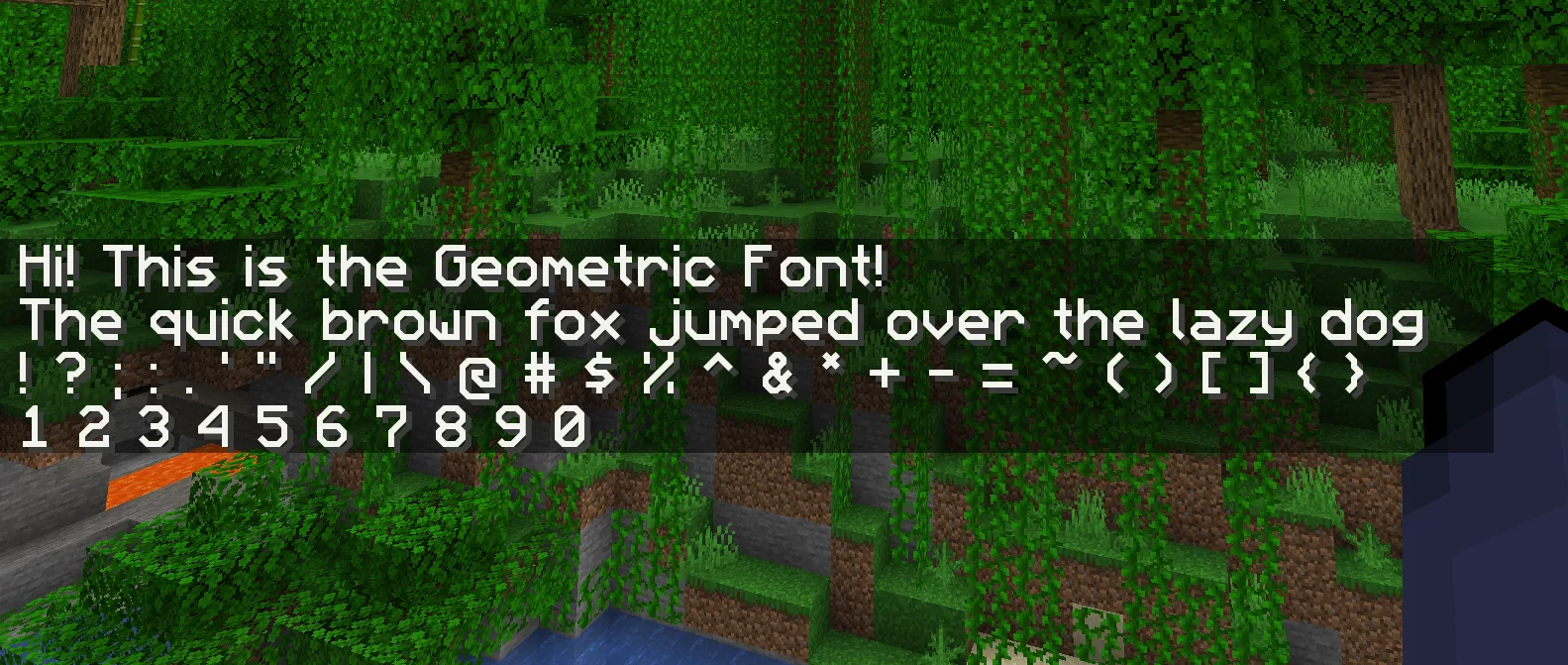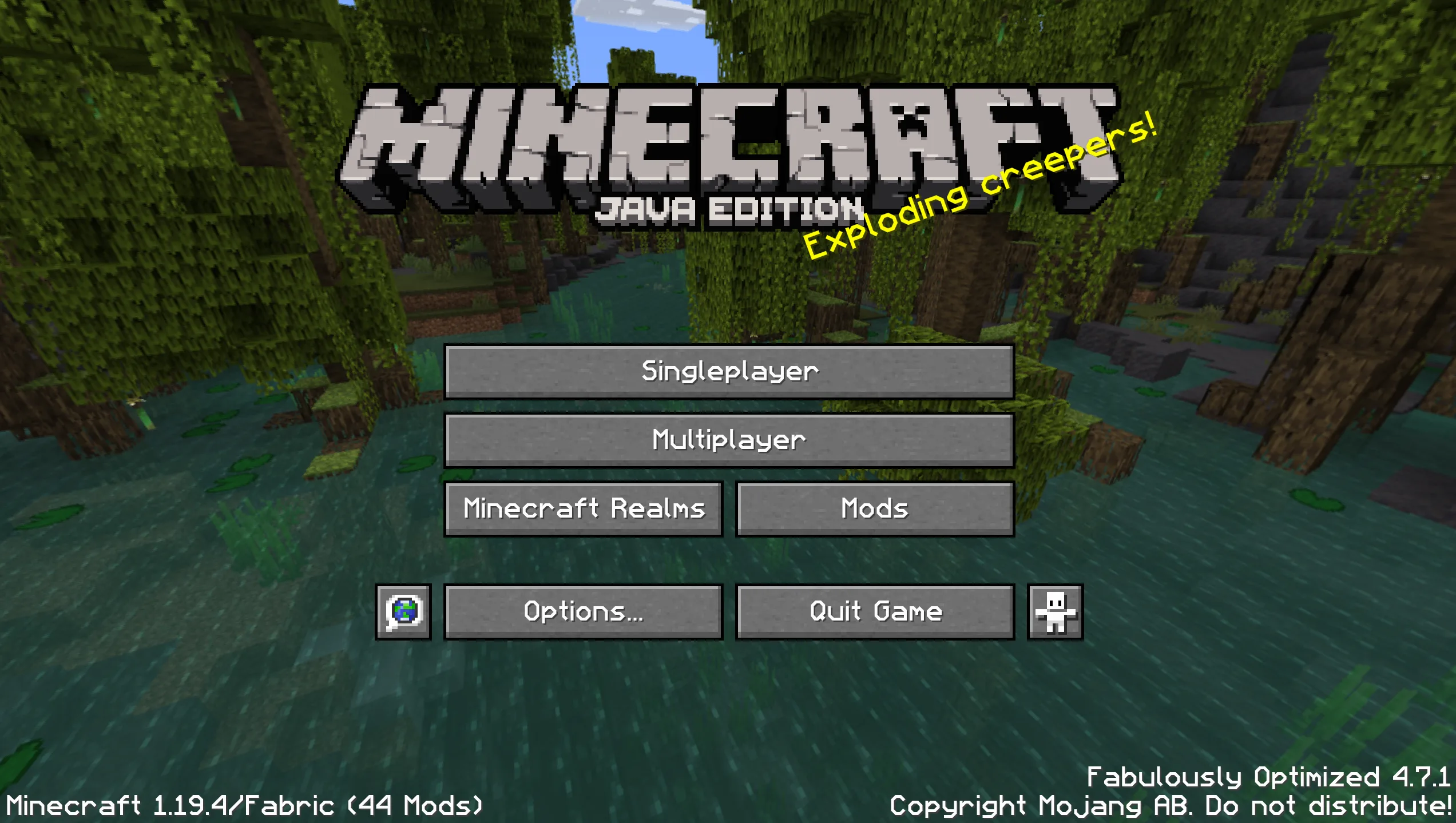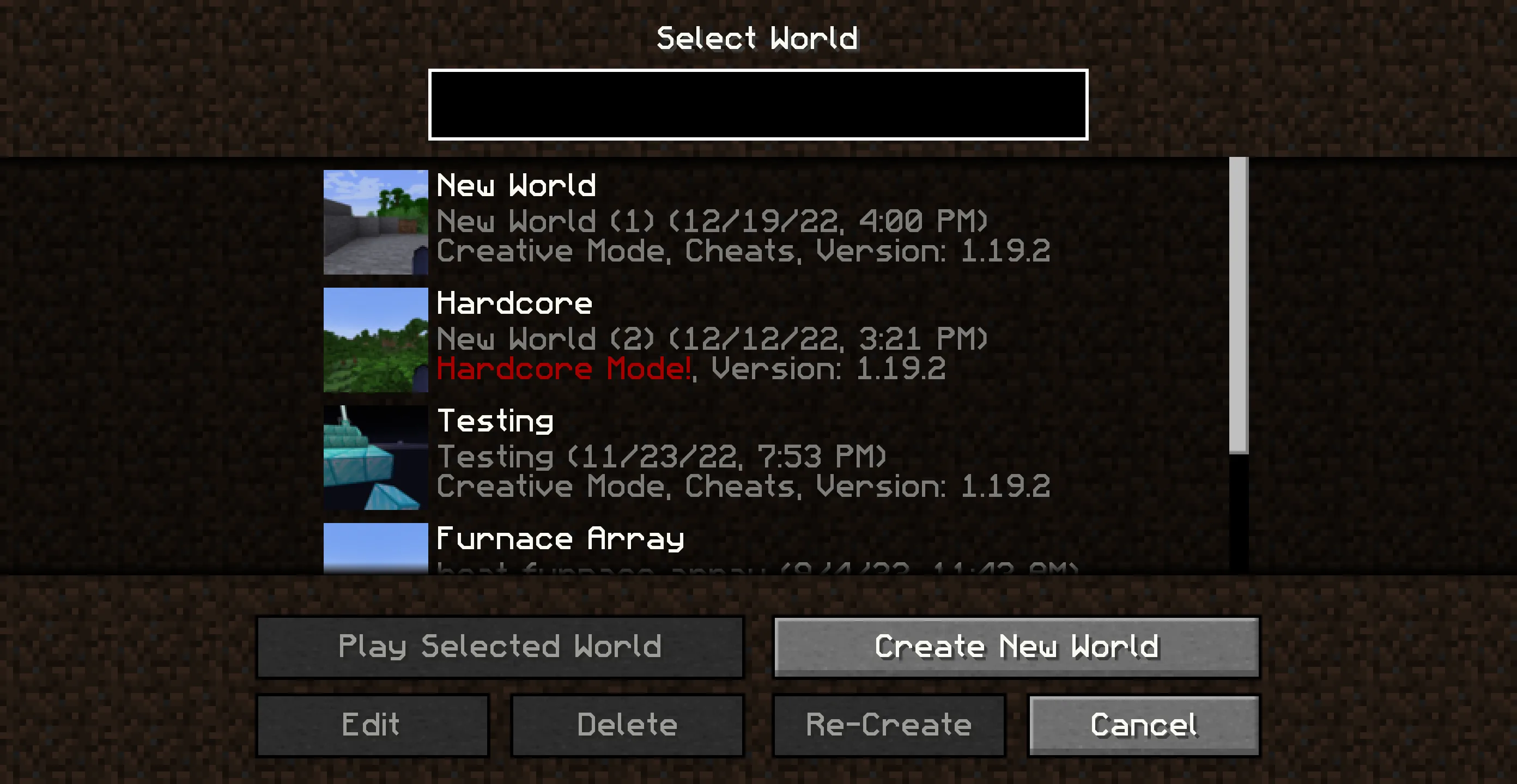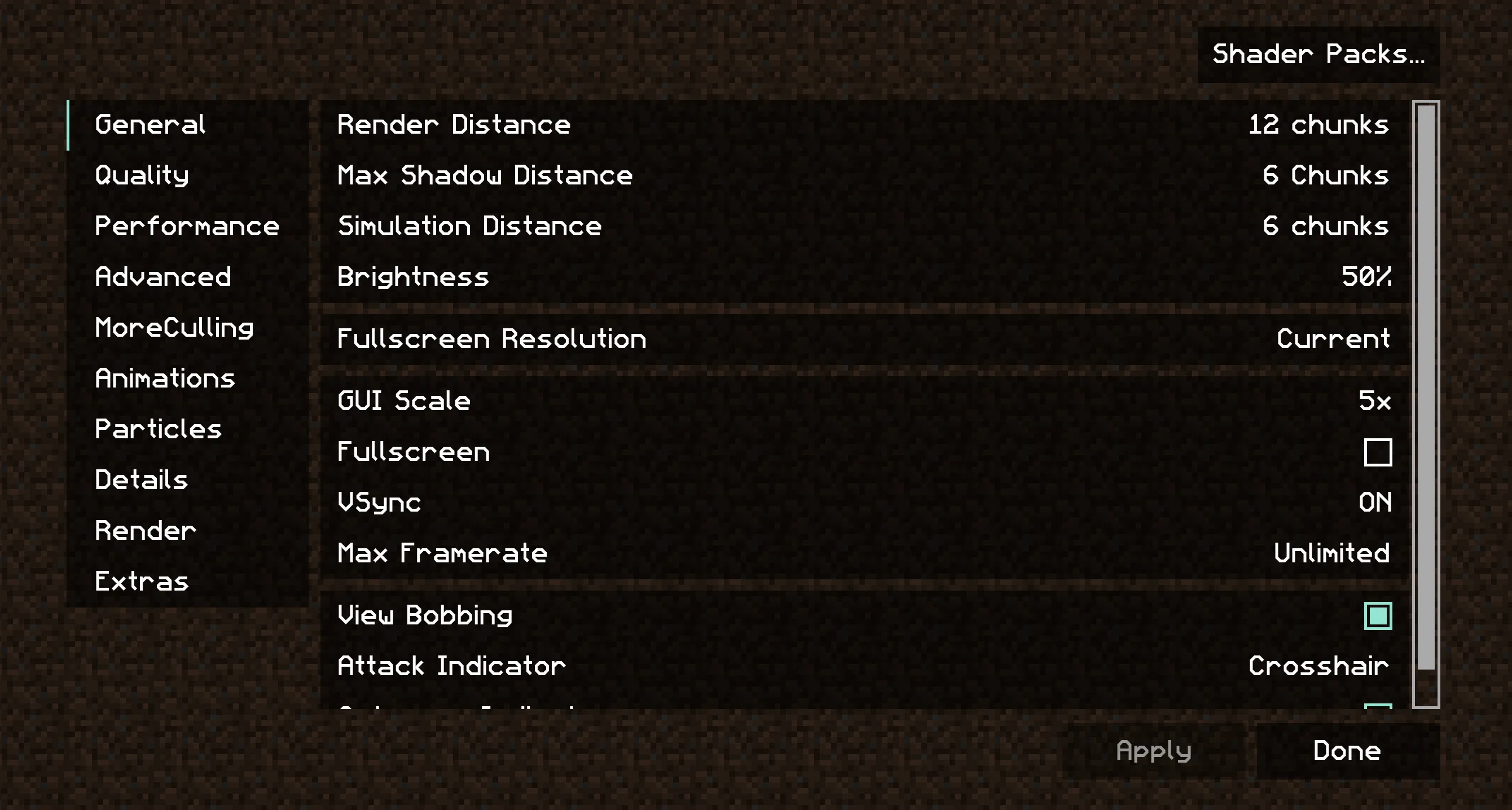
Geometric Font 2
Чистый и чёткий ремейк стандартного шрифта Mojangles для всех разрешений, включая поддержку Caxton.
Этот ресурспак предлагает острый и чистый ремейк стандартного шрифта Mojangles, подходящий для всех разрешений экрана. В отличие от многих других HD-шрифтов, которые используют растровые изображения и могут выглядеть неровно, этот шрифт сохраняет чёткость при любом масштабе интерфейса, что лучше сочетается с ванильным стилем Minecraft.
Geometric Font 2 — это полностью переработанная версия оригинального шрифта с полной поддержкой OpenType и улучшенной согласованностью. Он обеспечивает резкую и современную визуальную эстетику, подходящую для различных версий игры, от 1.20.3 до 1.21.7.